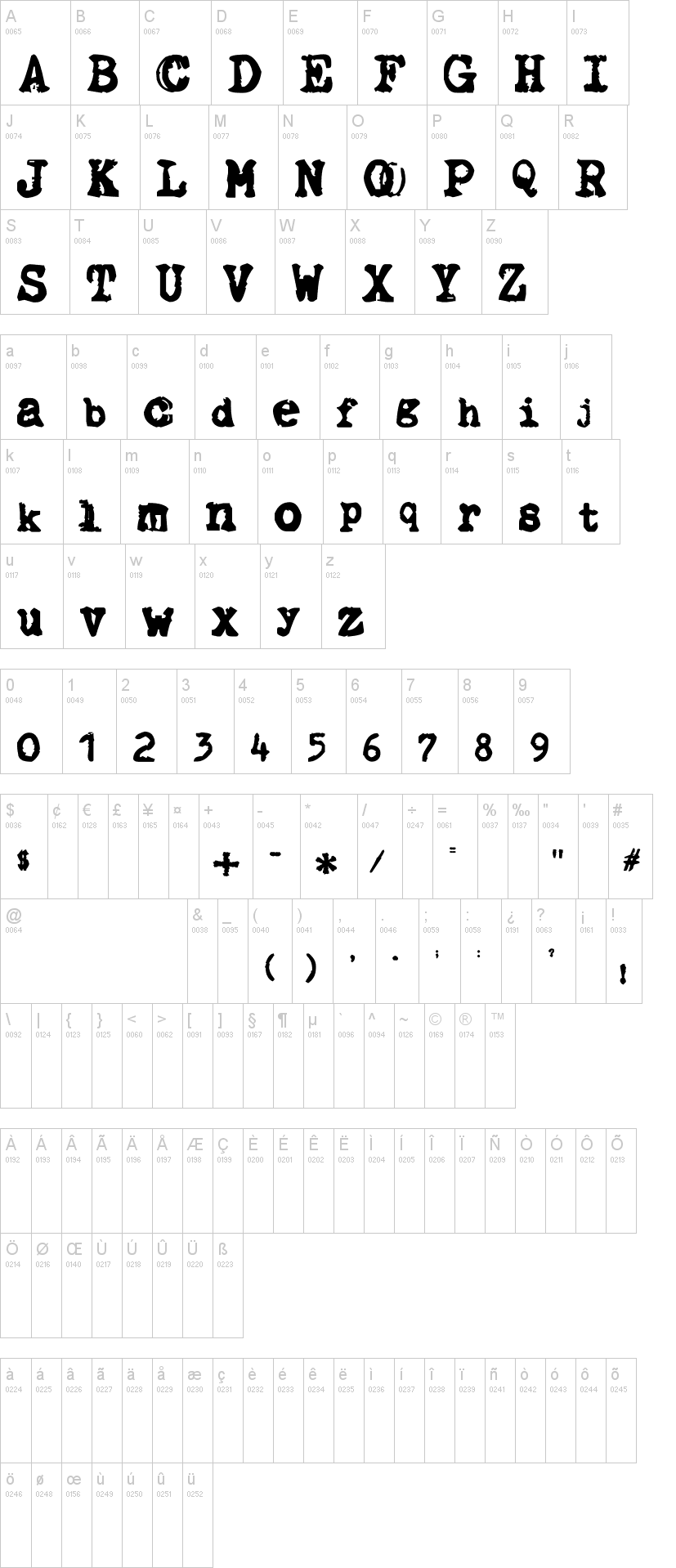
The Libertines
Gersan Borge A
esta font fue creada con una maquina olimpia 2 y se la dedico a una de las mejores bandas de el genero post punk revival the libertines.